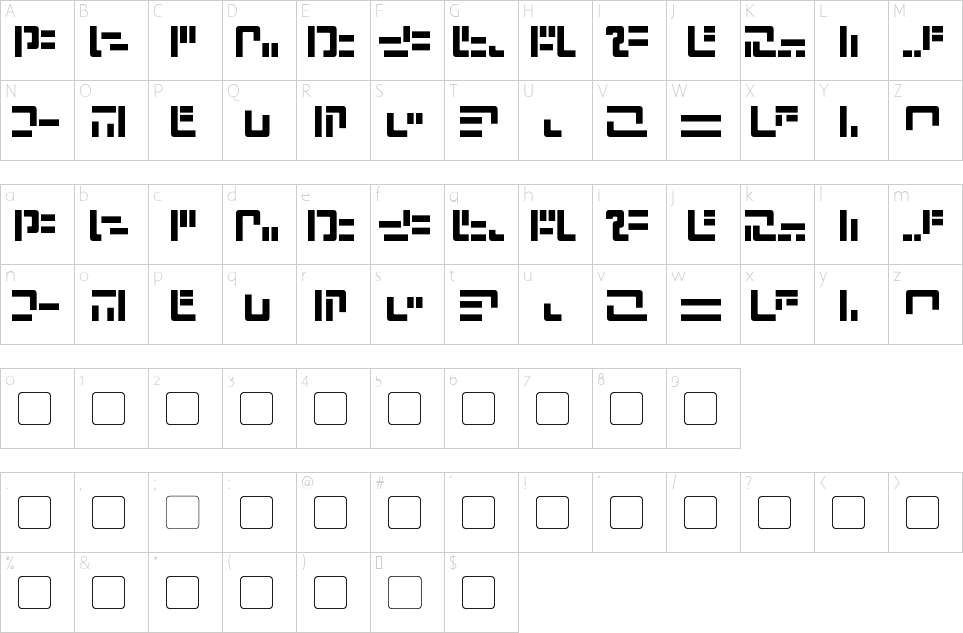
A fonte Modern Iaconic é uma escolha ótima para designers gráficos e profissionais que buscam uma fonte moderna e minimalista. Desenhada pelo Pixel Sagas – Neale Davidson, esta fonte gratuita foi projetada para agregar elegância e simplicidade a qualquer projeto. Modern Iaconic é perfeitamente adaptada para a escrita em blogs, sites, e projetos gráficos, proporcionando uma aparência clean e profissional. Com seus 5,754 downloads, a fonte provou ser popular e valiosa entre os designers. Seja você um iniciante ou um profissional, Modern Iaconic é uma fonte que oferece um valor real para seu trabalho. Descubra por si mesmo o poder desta fonte moderna e elegante.